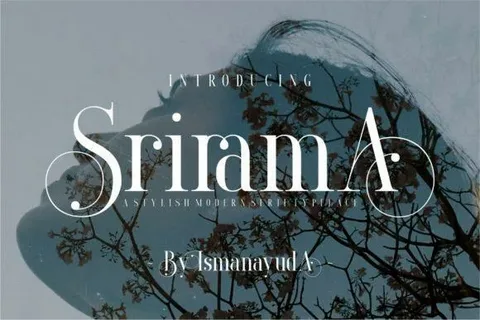
[Creativefabrica] Srirama Font (2021)
Srirama
- это детальный и элегантный шрифт с засечками.
Он потрясающе смотрится на свадебных приглашениях, благодарственных открытках, цитатах, поздравительных открытках, логотипах, визитных карточках и любом другом дизайне, требующем индивидуального подхода.